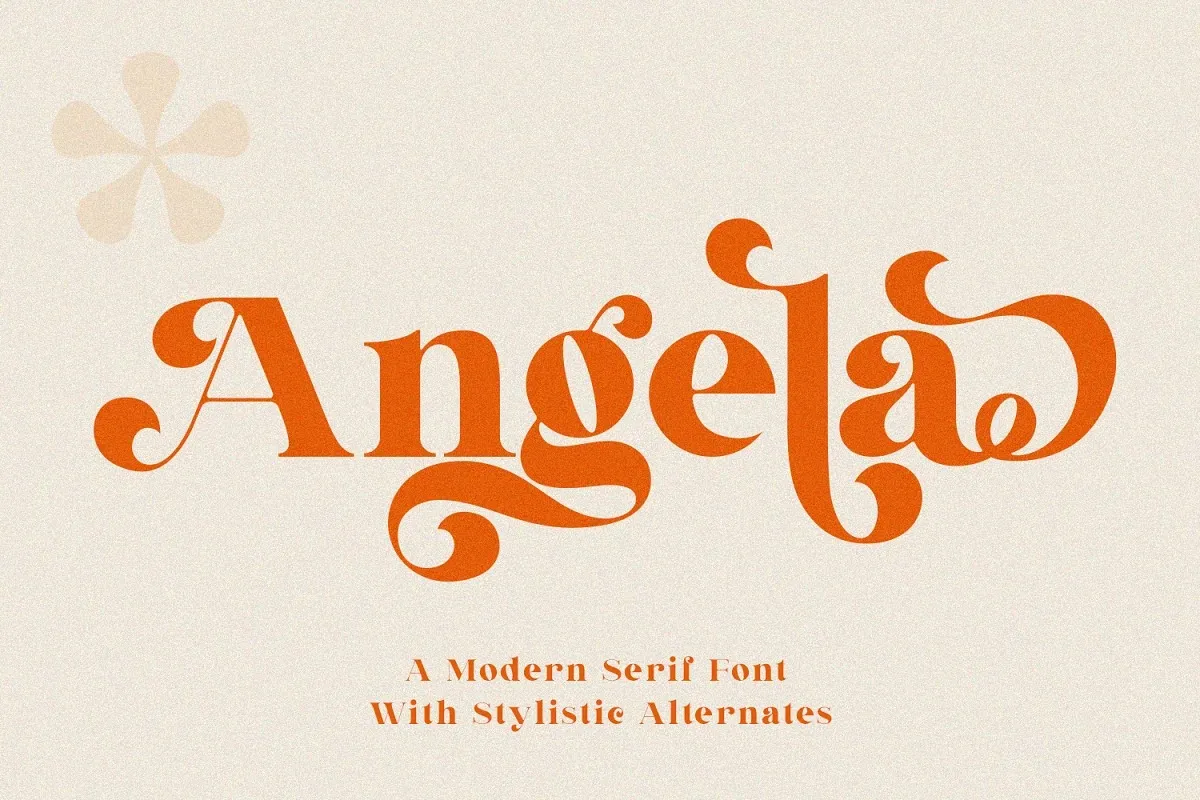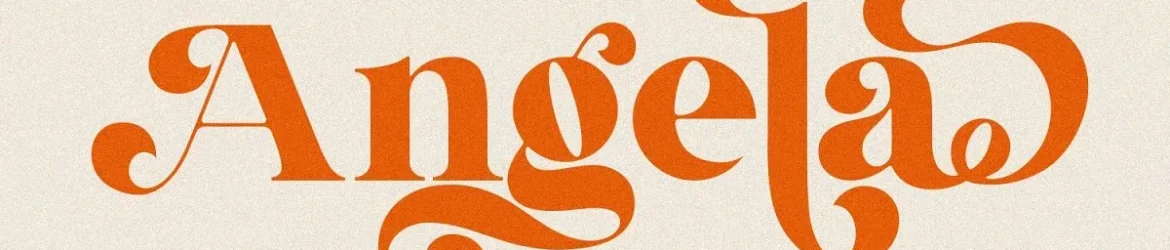
A Angela Font é uma elegante tipografia serif criada por Sealoung com detalhes únicos que mesclam formas geométricas com curvas orgânicas. Esta fonte perfeita para várias aplicações, como anúncios, identidades de marca, logotipos, embalagens, títulos e headlines, bem como designs editoriais. A Angela oferece um toque sofisticado e delicado que se ajusta a uma variedade de mídias visuais, tornando-a uma escolha irresistível para projetos profissionais de alto padrão. Compreender o equilíbrio entre formas rectas e curvas suaves da Angela é como ter um amigo fiel que traz brilho aos teus projetos, proporcionando um toque refinado que não se esgota em qualquer tipo específico.